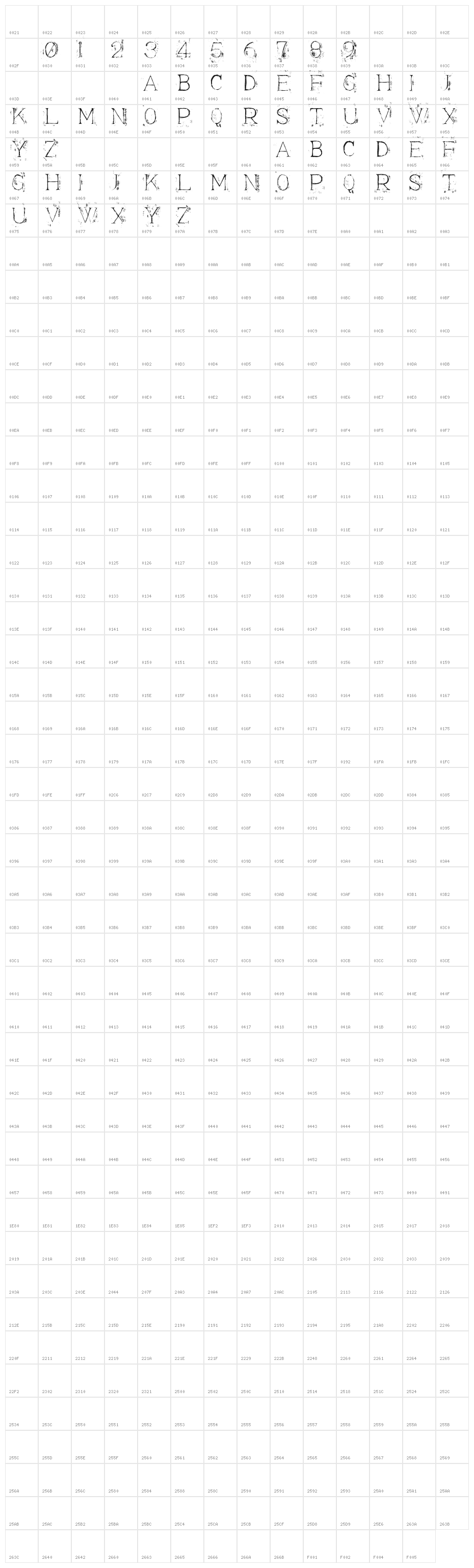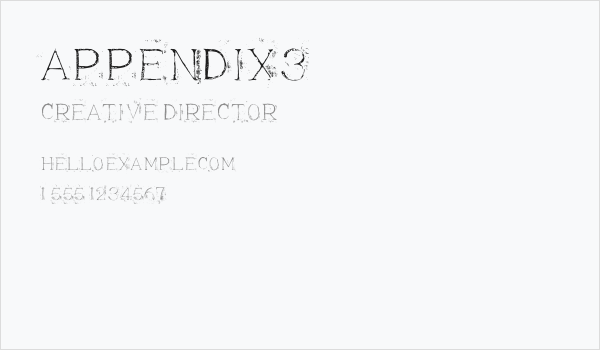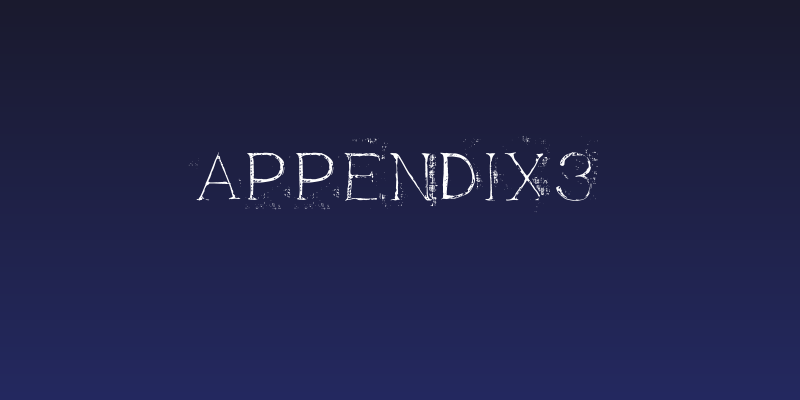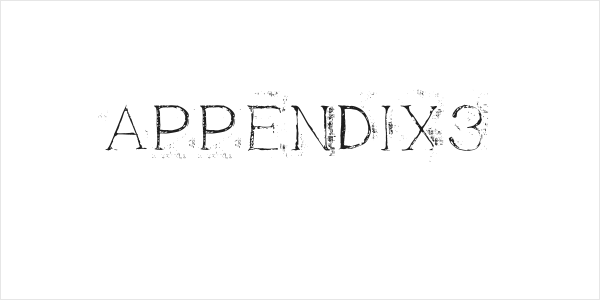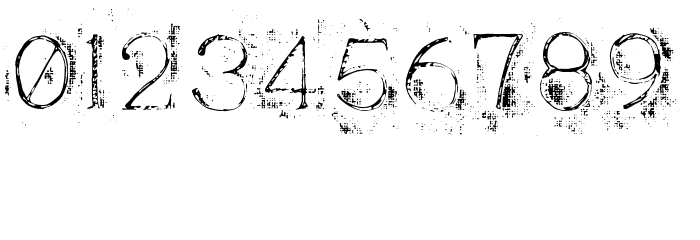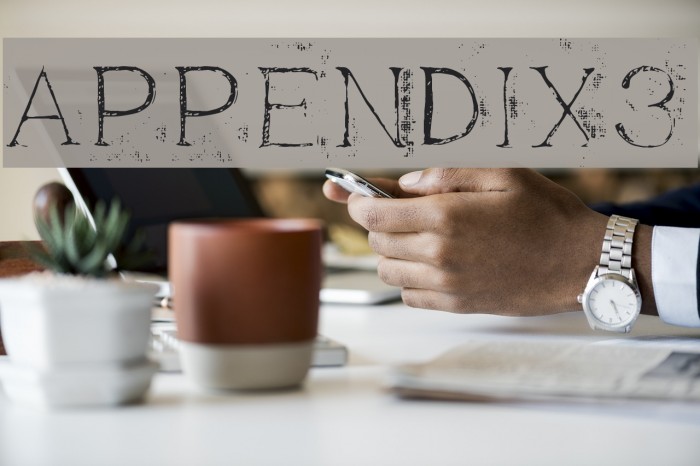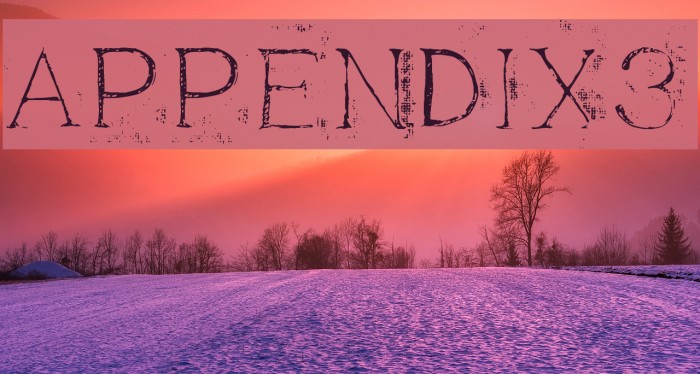
Appendix3 Font
✎ Distorted Eroded
| समग्र शैली | Vintage |
| उपयोग का मामला | Headlines, Logos, Decorative text |
| सुझाए गए प्रोजेक्ट | Ideal for vintage posters, retro-themed branding, rustic wedding invitations, and any design needing an antique touch. |